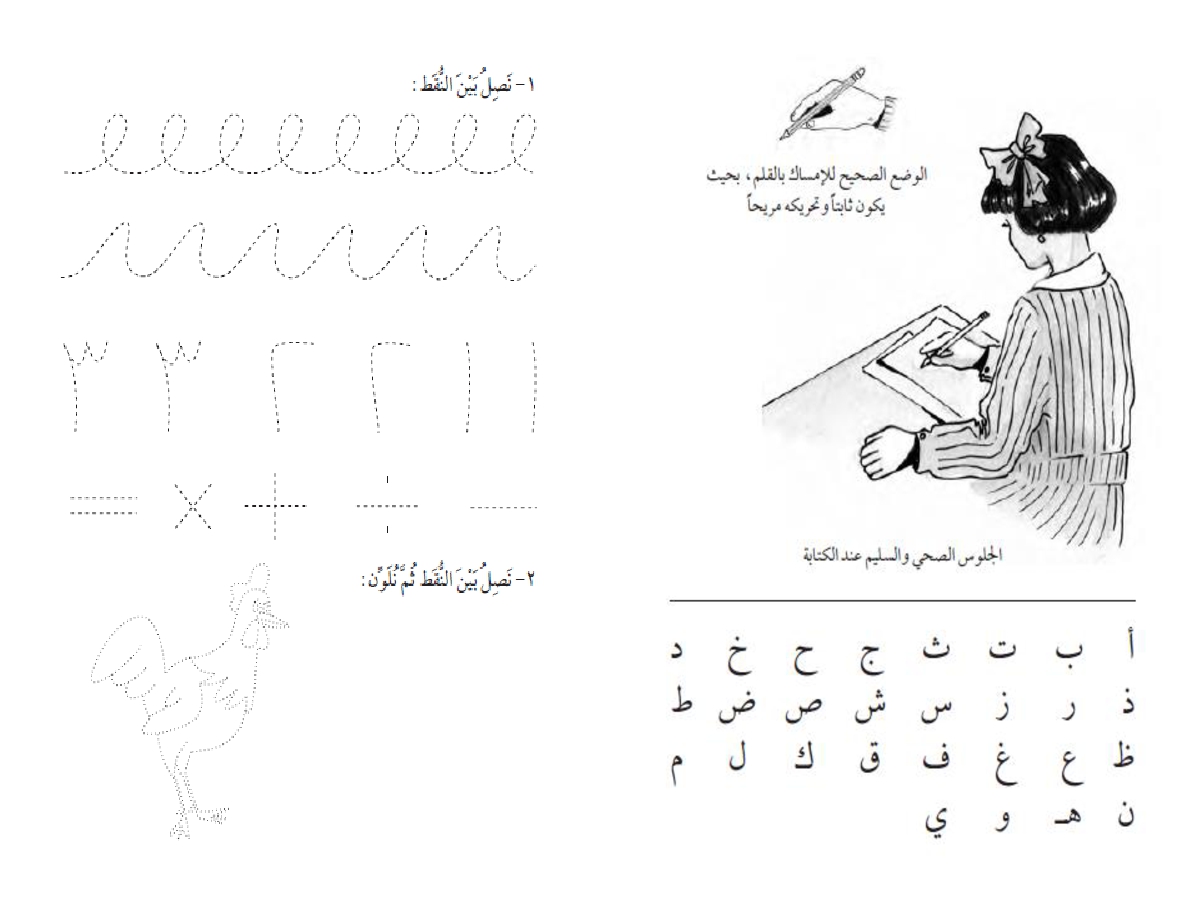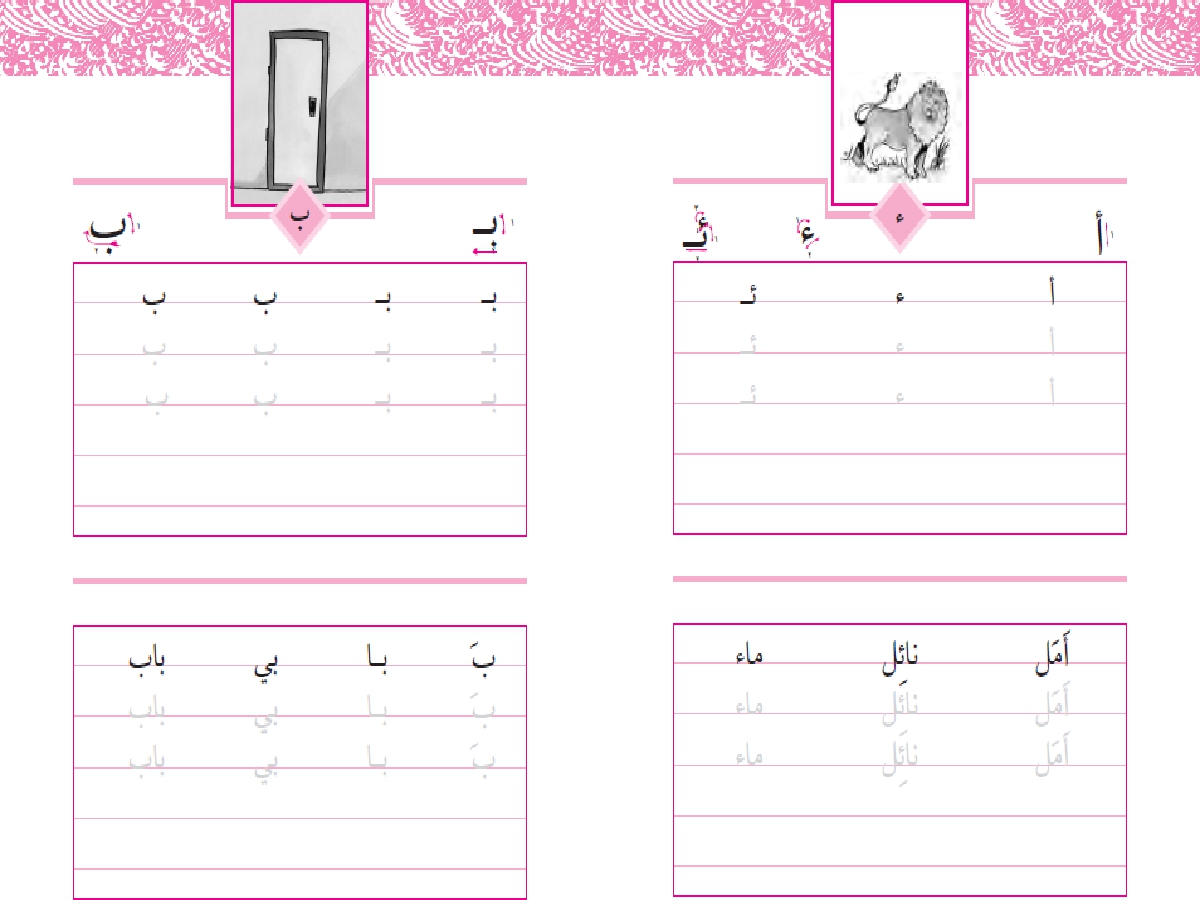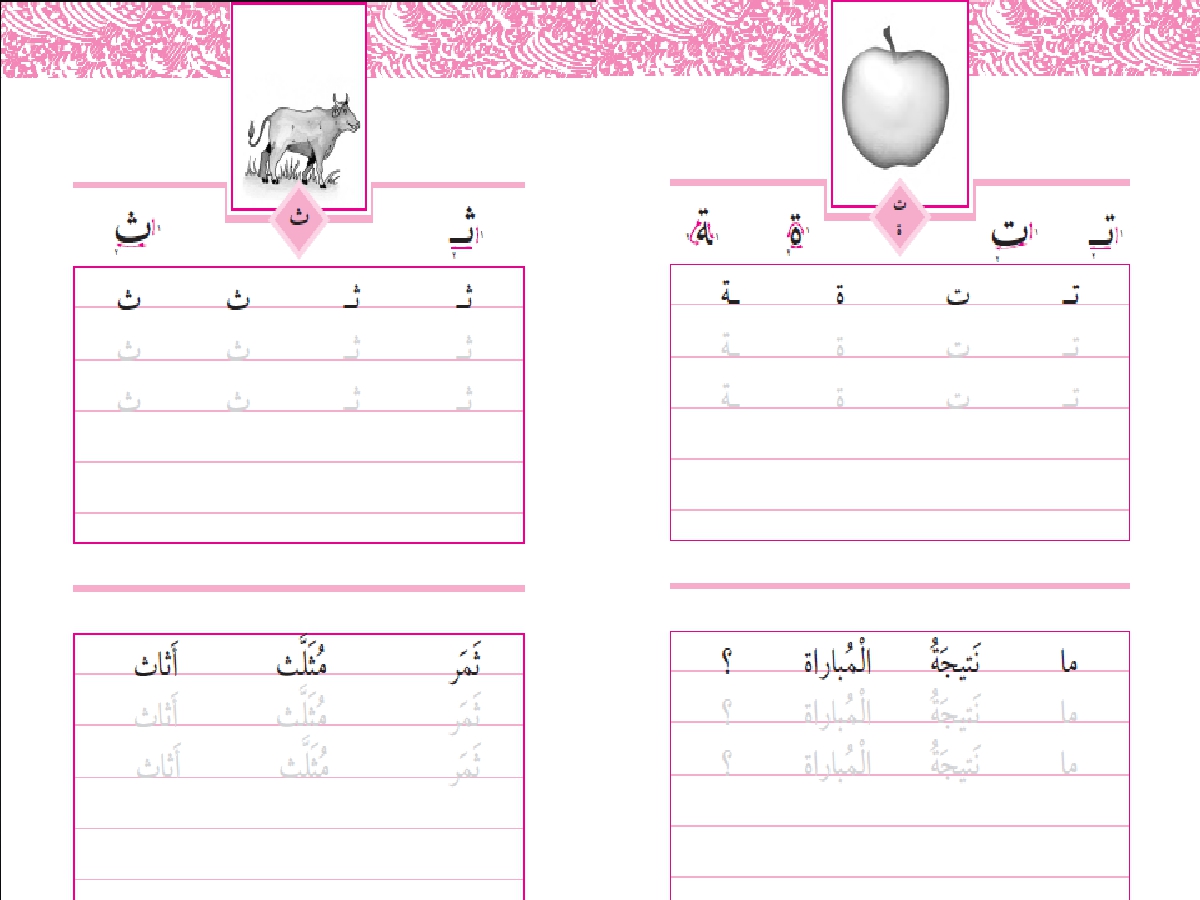
لطالما نظر الاب إلي ابنه ووجد خطه غير جميل وغير منظم
وحاول بشتي الطرق أن يجعل خطه أحسن ولكن كل محاولاته
كانت بلا جدوي .
نقدم لكم اليوم كراسة جميلة للخط للصفوف الأولي مع بعض
النصائح الذهبية لجعل خط أبنك جميلا :
1- عليك بكثرة الكتابة فانها تظهر موهبة ابنك في الكتابة
وتحسن من خطه
2- حاول ان تكتب وأنت في وضعية مريحة فالكتابة في وضعية
مزعجة يجبرك علي الكتابة بخط سيء
3- عند الكتابة التزم بالسطر وحاول علي الا تخرج عنه
4- يجب أن تراعي الحروف التي تكتب فوق السطر والحروف
التي تكتب تحت السطر والحروف التي تكتب علي السطر
5- يجب مراعاة علامات الترقيم ووضعها في أماكنها المناسبة
6- يجب أن تترك فراغات مناسبة بين كل حرف وحرف وبين كل
وبهذا نكون قد انتهينا من بعض النصائح لخط جميل الان نترككم
مع صور من كراسة الخط